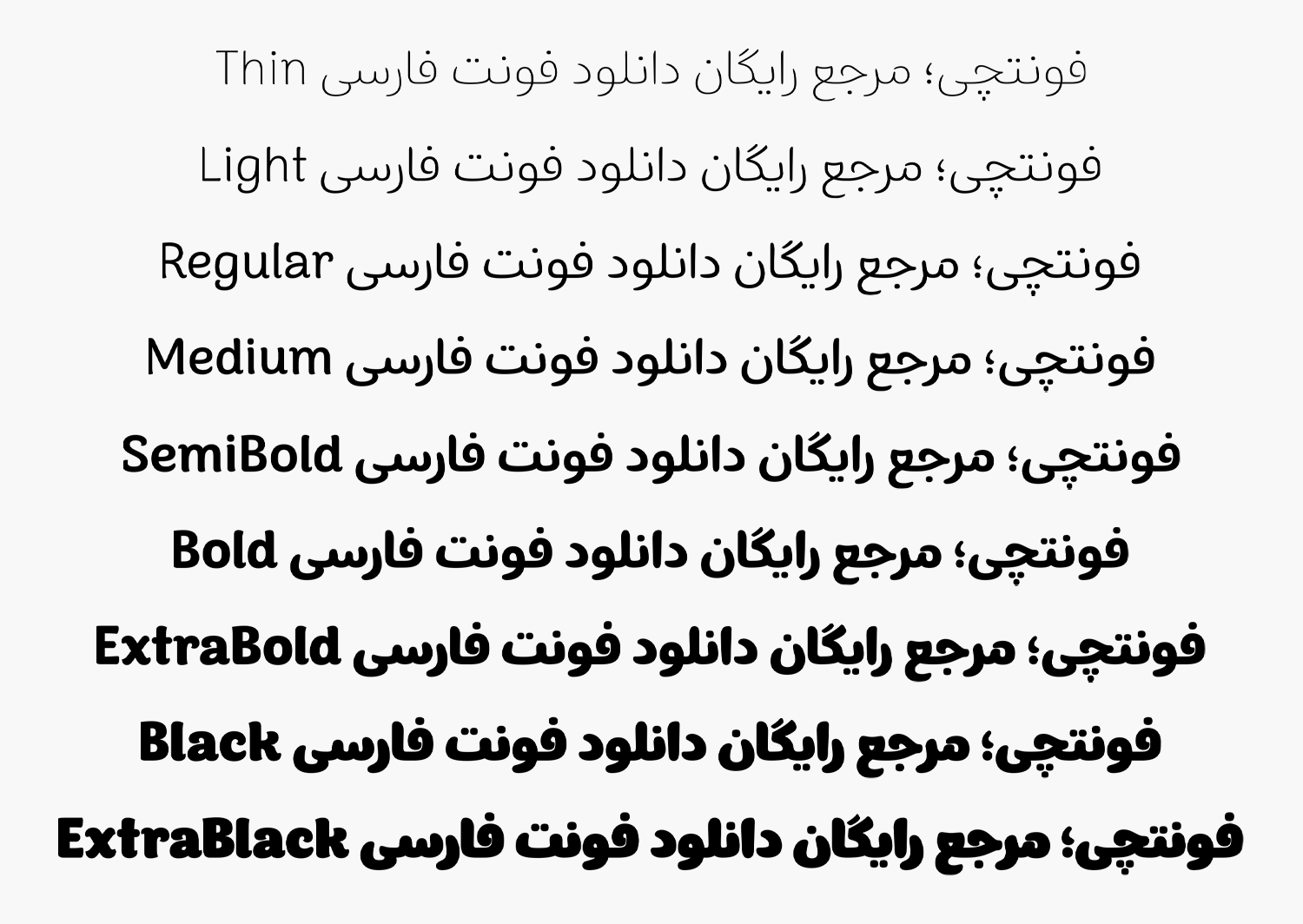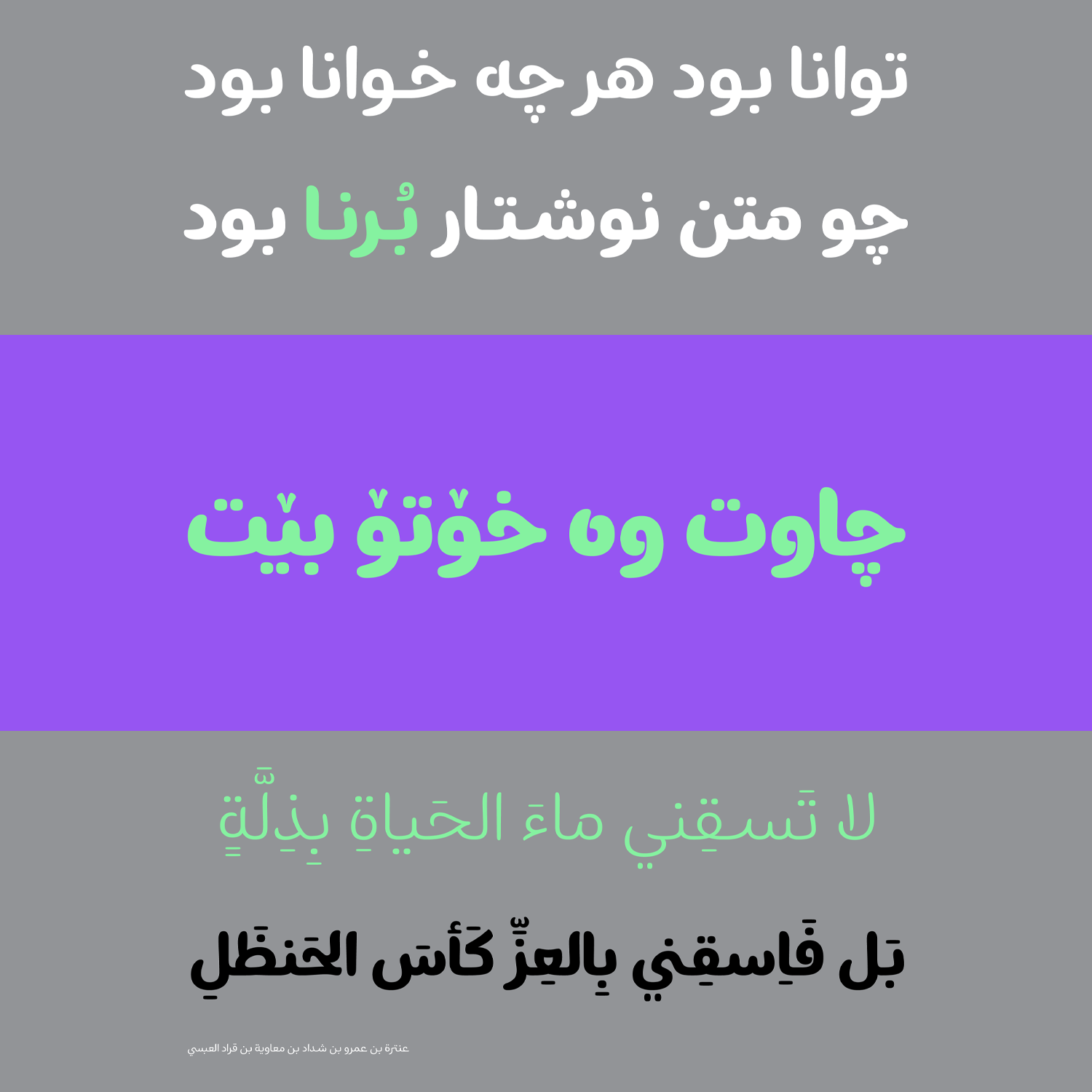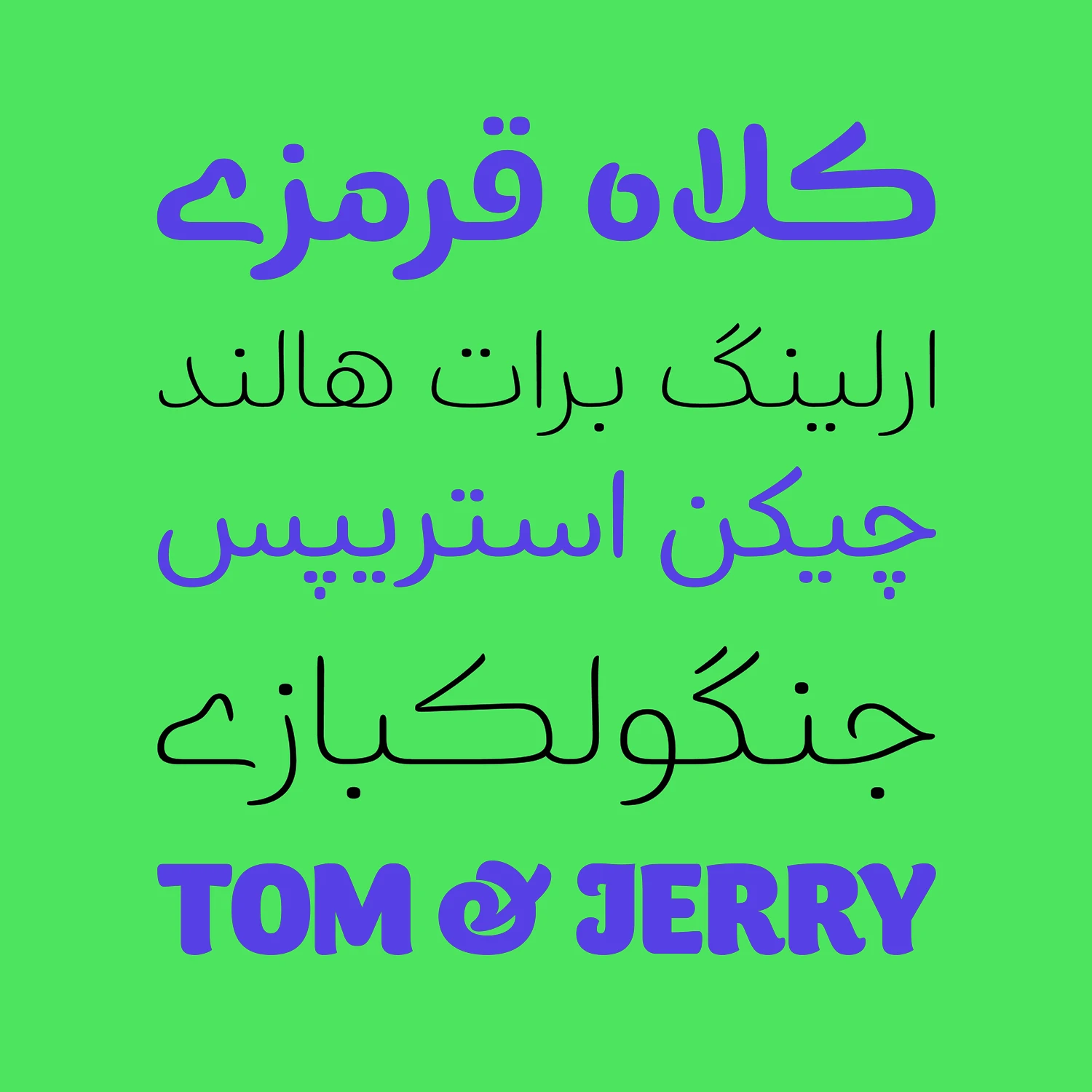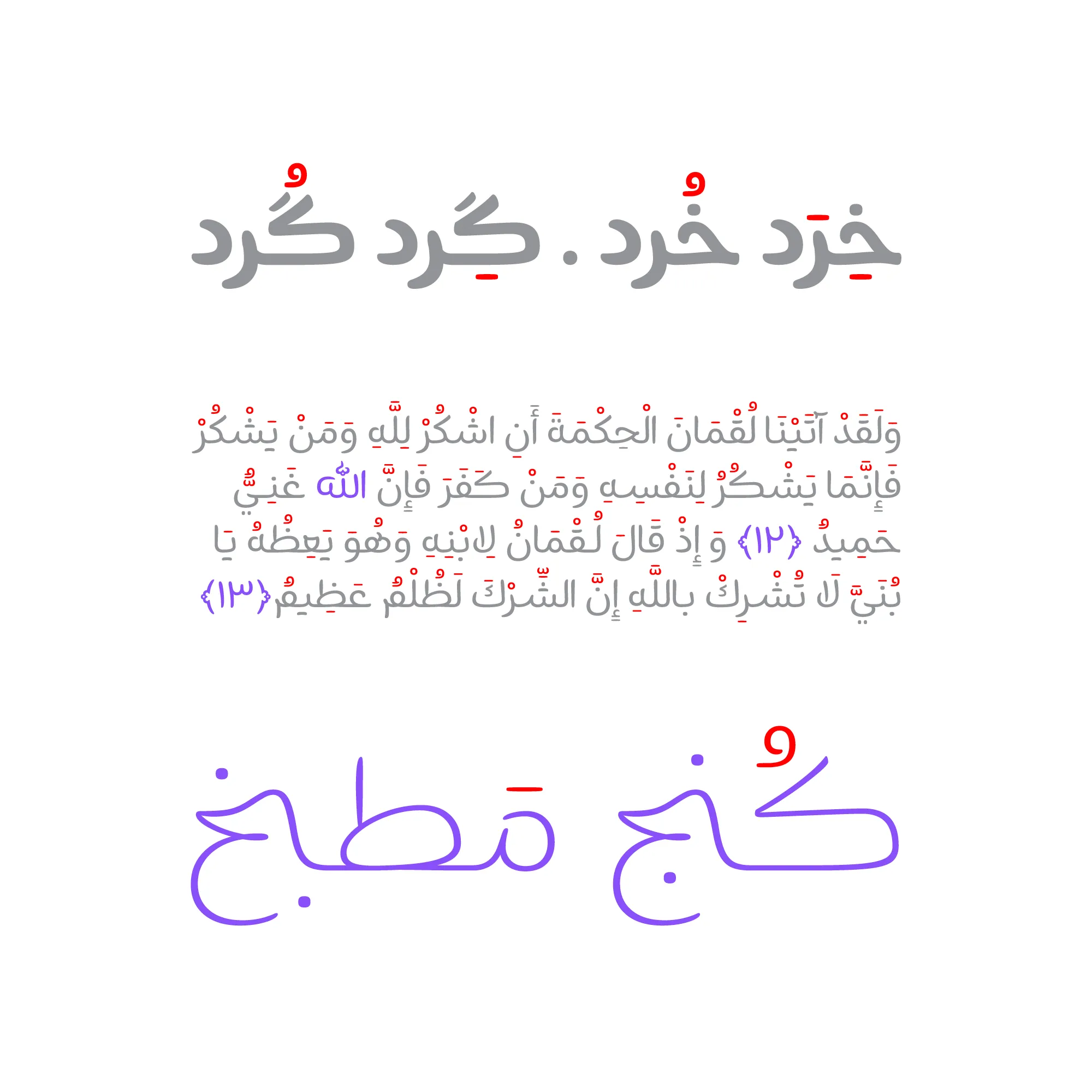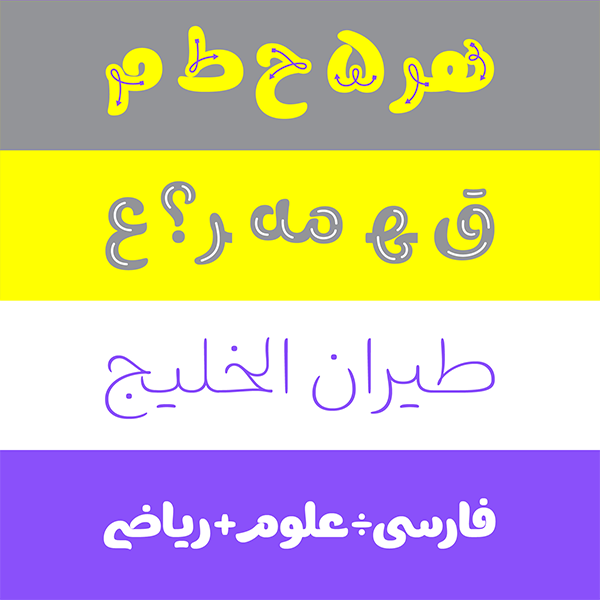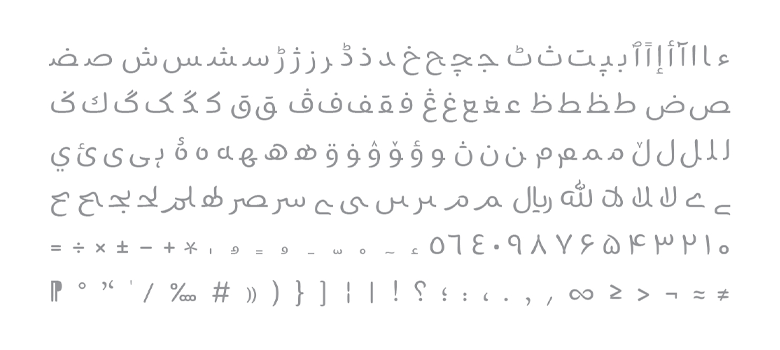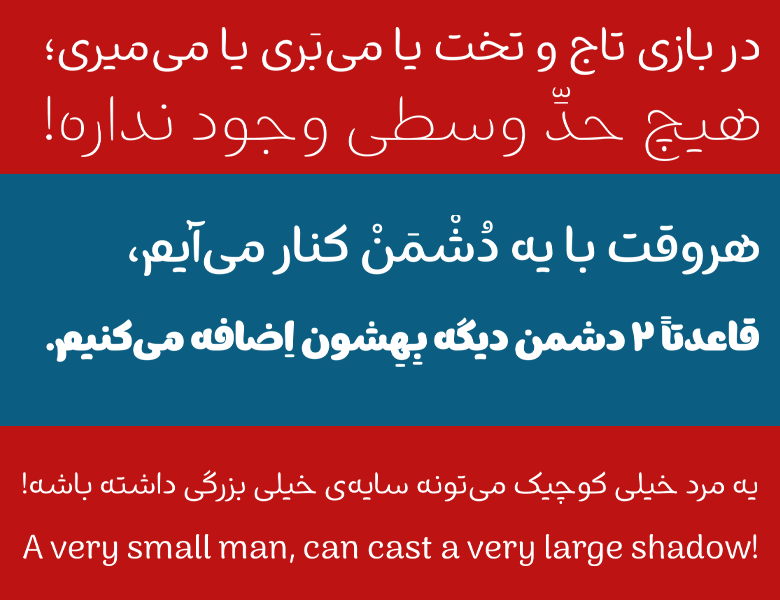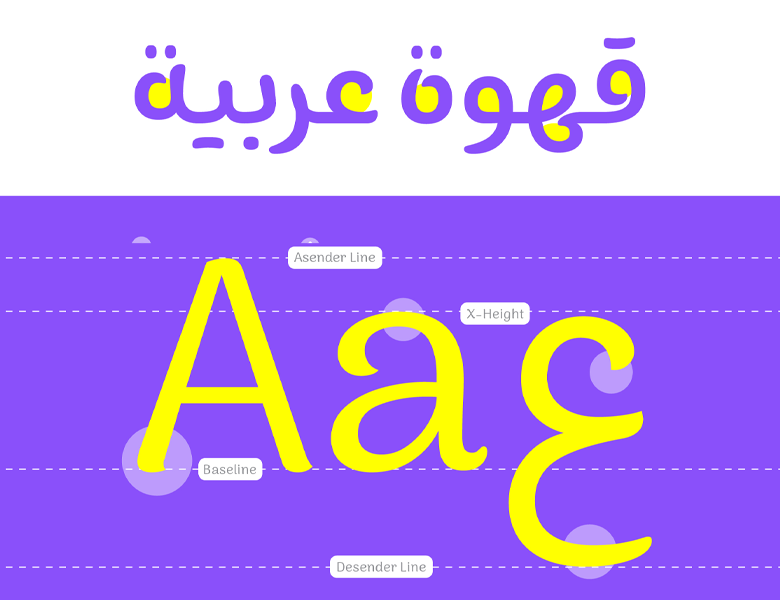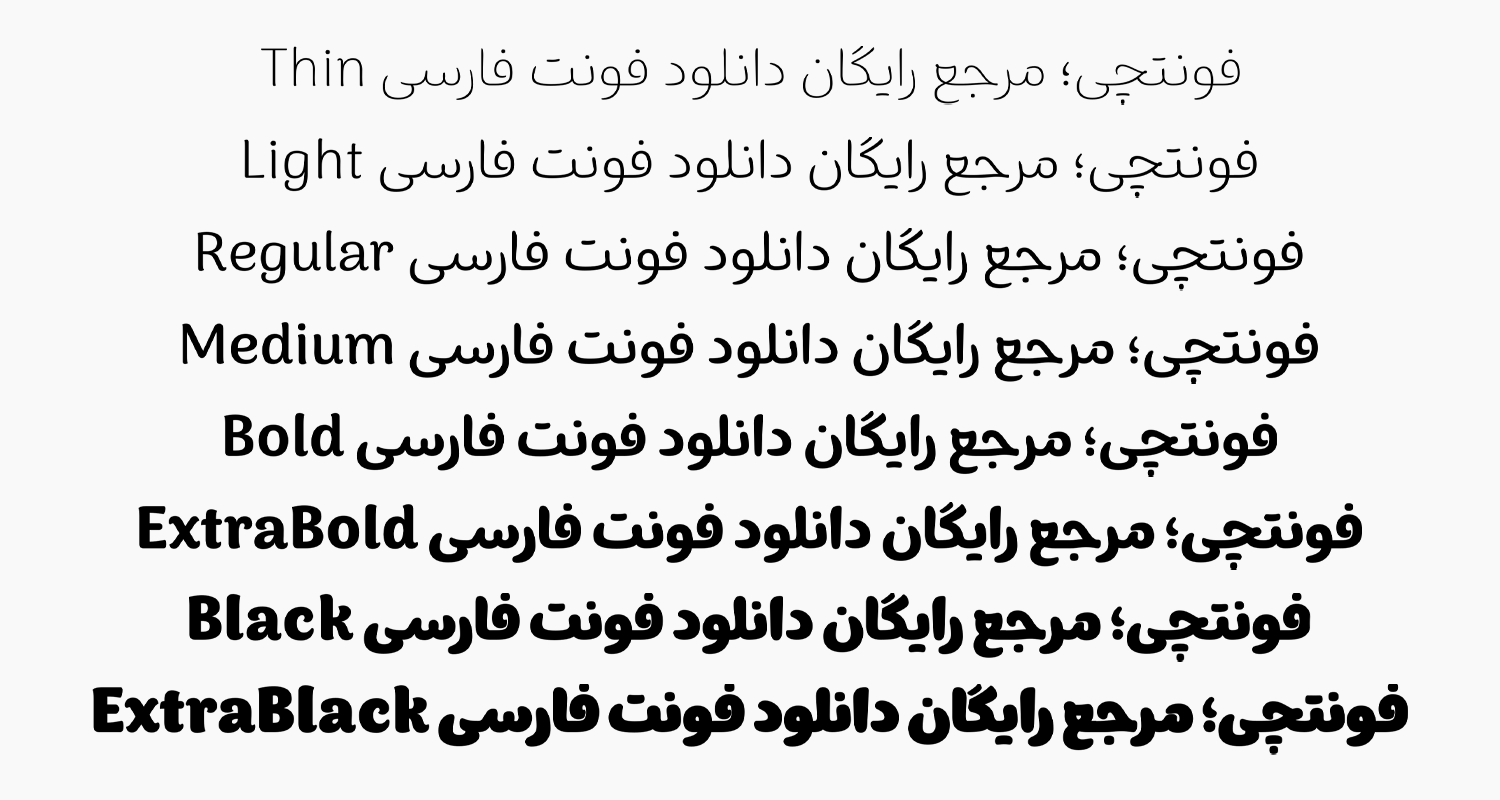
فونت برنا (Borna)
فونت برنا (Borna) با ظاهر نمایشی و ساختاری نرمو لطف که دارد مناسب متن است. از این فونت دست نویس که الهام گرفته از خط کوفی مغربی است، میتوان در متنهای نسبتا بلند استفاده کرد. شاید بهترین جایی که بتوان از این فونت استفاده کرد برای قصهگویی در کتاب کودک و نوجوان باشد که ظاهر دستنویس و دوستانه این فونت، حس صمیمیت بیشتری را بهارمغان میآورد.
این فونت شامل ۹ وزن با پشتیبانی از نسخه وریبل است که دارای ظاهری بازیگوش با دندانههایی پر از حس کودکی و سرزندگی است. منحنیهایی با پیچ و تاب زیاد که گویی موی جعد دختران خردسالی است که به باد سپرده شده است. چشمها نیز در این فونت حس پویایی مرز بین کودکی و نوجوانی را زنده نگه داشته است که جنبوجوش زیادی به این فونت داده است.
در ادامه این نوشته از وبسایت فونتچی میخواهیم به نقد و بررسی کامل فونت برنام بپردازیم؛ با دانلود فونت فارسی برنا میتوانید از آن برای طراحی انواع کتاب کودک، مجلات سرگرمی یا استفاده در سایت و اپلیکیشنهایی که مخصوص کودکان است، حس صمیمیت را برای آنها دو چچندان کنید که از خواندن داستانهای مصور نهایت لذت را ببرند.
معرفی و بررسی فونت برنا (Borna)
فونت Borna در دسته فونتهای نمایشی و فانتزی قرار دارد که کلیت ظاهر آن به صورت دست نویس طراحی شده است. در طراحی این فونت برای تمامی حروف و وزنها از یک پهنای ثابت استفاده شده است که صرفا در بخش انتهایی و دندانه حروف این پهنا مقداری کاسته شده و ظاهری نمایشیتر به قلم داده است.
دندانهها و منحنیها با زاویهای صمیمی طراحی شده و چشمیها نیز در همه وزنها گاه دارای ظاهری کشیده و گاه ظاهری کوچک است که خود نشان از حس چابکی این فونت دارد.
از این فونت جدای از کتاب کودک و نوجوان، میتوان در طراحی انواع بیلبورد استفاده کرد. یا در فضای دیجیتال میتوان در طراحی انواع بنرها و اسلایدرهایی که باید ظاهری صمیمی داشته باشند آن را در لیست فونتهای اصلی قرار داد.
وزن و سبک طراحی فونت برنا
ظاهر فونت برنا در تمامی وزنهای ۸ گانه آن رعایت شده است. این فونت در حال حاضر که نسخه اول آن منتشر شده، وزن نازک تا خیلی سیاه را شامل میشود که در تمامی وزنها به دلیل ساختار دستنویس بودن نقطهها بهصورت جدا ازهم طراحی نشدهاند.
همچنین با توجه به پشتیبانی از زبانهای مختلف که جدای از حروف اصلی هر زبان شامل کاراکترهای خاص و تزئینی میشود، از اعداد متناسب با آن زبان نیز پشتیبانی میکند که با دارا بودن نسخه اعداد هک شده فارسی و عربی، در چند گروهبندی مختلف بر این اساس نیز طبقهبندی شده است.
ویژگی و مشخصات فونت Borna
پیش از دانلود فونت برنا بد نیست نگاهی به ویژگیها و امکاناتی که این فونت دست نویس برای زیبا سازی متون در تمامی وزنها و زبانها در اختیار قرار داده است داشته باشیم.
پشتیبانی از ۵ زبان مختلف
فونت برنا فارسی از معدود فونتهایی است که علاوه بر این زبان، از ۴ زبان دیگر شامل عربی، انگلیسی، کردی و اردو نیز پشتیبانی میکند. پشتیبانی از این زبانها صرفا محدود به حروف اصلی نبوده و شامل کاراکترهای اعداد، حروف و تزئینی نیز میشود.
به دلیل ترکیبات متنوعی که در هر زبان وجود دارد که گاها مشترک هستند، فایل این فونت شامل پشتیبانی همه زبانها میشود و جداسازی آن بر اساس زبان لاتین و خاورمیانهای صرفا بر اساس اعداد و اعراب صورت گرفته که در این نسخهها تغییرات جزئی را دارند.
برای نسخه انگلیسی این فونت طراحی جدی بر اساس طراحی زبان فارسی در نظر گرفته نشده و از فونت انگلیسی محبوب Arima Madurai الهام گرفته شده است که صرفا تغییراتی جزئی در آن داده شده و صدالبته به منظور هماهنگی در تمامی وزنها یک بازطراحی در وزنهای سنگین نیز صورت گرفته است.
وریبل فونت برنا با متغیر وزن
در بسته حرفهای فونت برنا به نسخه وریبل دسترسی خواهید داشت. این نسخه از فونت دارای تمامی وزنهای ۸ گانه در قالب یک فایل یکپارچه است که بدون نیاز به نصب وزنهای متعدد که هر یک در یک فایل مجزا در نظر گرفته شده، میتوانید فقط با نصب یک فایل فونت به تمامی وزنهای این فونت دسترسی داشته باشید.
فونت متغیر برنا در نسخه ۲.۰ به این قلم افزوده شده است؛ بنابراین فعلا دارای یک متغیر وزن برای تغییر وزن است که میتوانید بسته به موقعیت استفاده شده در محیط وب از طریق کدهای CSS و در نرمافزارهای گرافیکی مانند فتوشاپ از طریق تنظیمات Open Type از هر یک از این وزنها استفاده کنید.
اما انتظار میرود که در نسخههای بعدی این فونت امکانات دیگری مانند سایر فونتها به نسخه متغیر برای تغییر سبک نقطهگذاری یا استفاده از اعراب رنگی افزوده شود.
تغییر رنگ اعراب روی حروف
در نسخه دوم فونت برنا قابلیتی کمنظیر در بین فونتهای فارسی اضافه شده است که میتوانید اعراب روی حروف را برای تمامی زبانهای فارسی، عربی، کوردی و اردو که دارای اعراب و کاراکترهای تزئینی هستند به صورت رنگی تایپ کنید.
همانطور که در تصویر بالا میبینید اعراب به رنگ قرمز تایپ شدهاند که بدون نیاز به انتخاب کاراکتر و تغییر رنگ کاراکترها در نرم افزارهای گرافیکی و ویرایشگر متن میتوانید به سادگی تمامی اعراب را به صورت رنگی تایپ کنید. در بسته دانلود فونت برنا راهنمای استفاده از این ویژگی برای تمامی نرمافزارها قرار داده شده است.
دارای حروف و ترکیبات جایگزین
این فونت نیز مشابه بسیاری از فونت های جدید فارسی از قابلیت حروف جایگزین نیز پشتیبانی میکند. یعنی مشابه چیزی که در تصویر زیر میبینید، میتوانید حروفی همچون «م، خ، ح، ی، ک، گ» را با ظاهری متفاوت تایپ نمود.
- امکان تغییر رنگ در حرکتگذاری حروف
- کامل شدن کارکترهای زبانهای عربی، کردی و اردو
- بازبینی فاصله گذاری حروف، اعداد و اعلائم